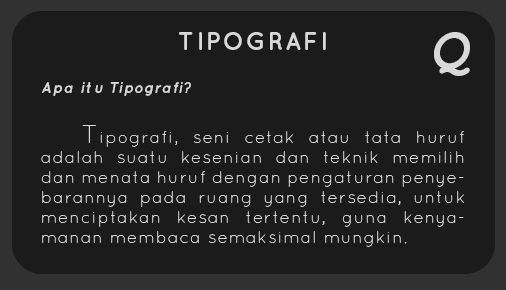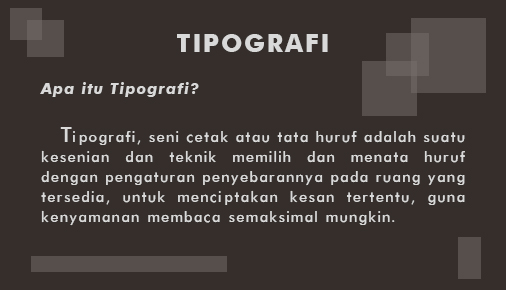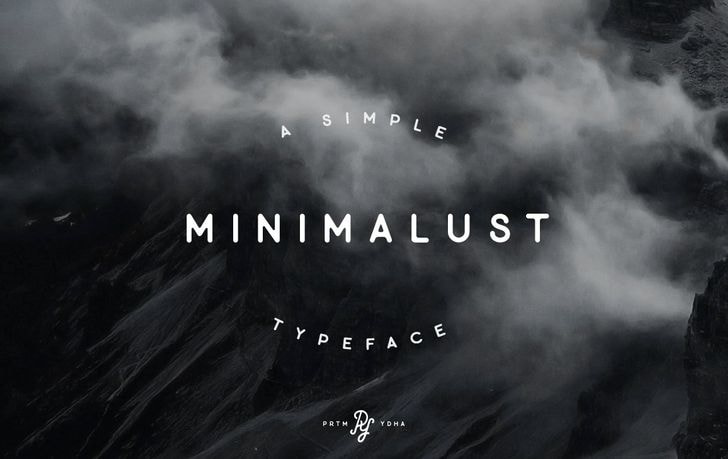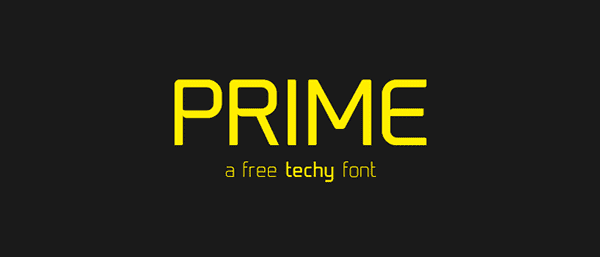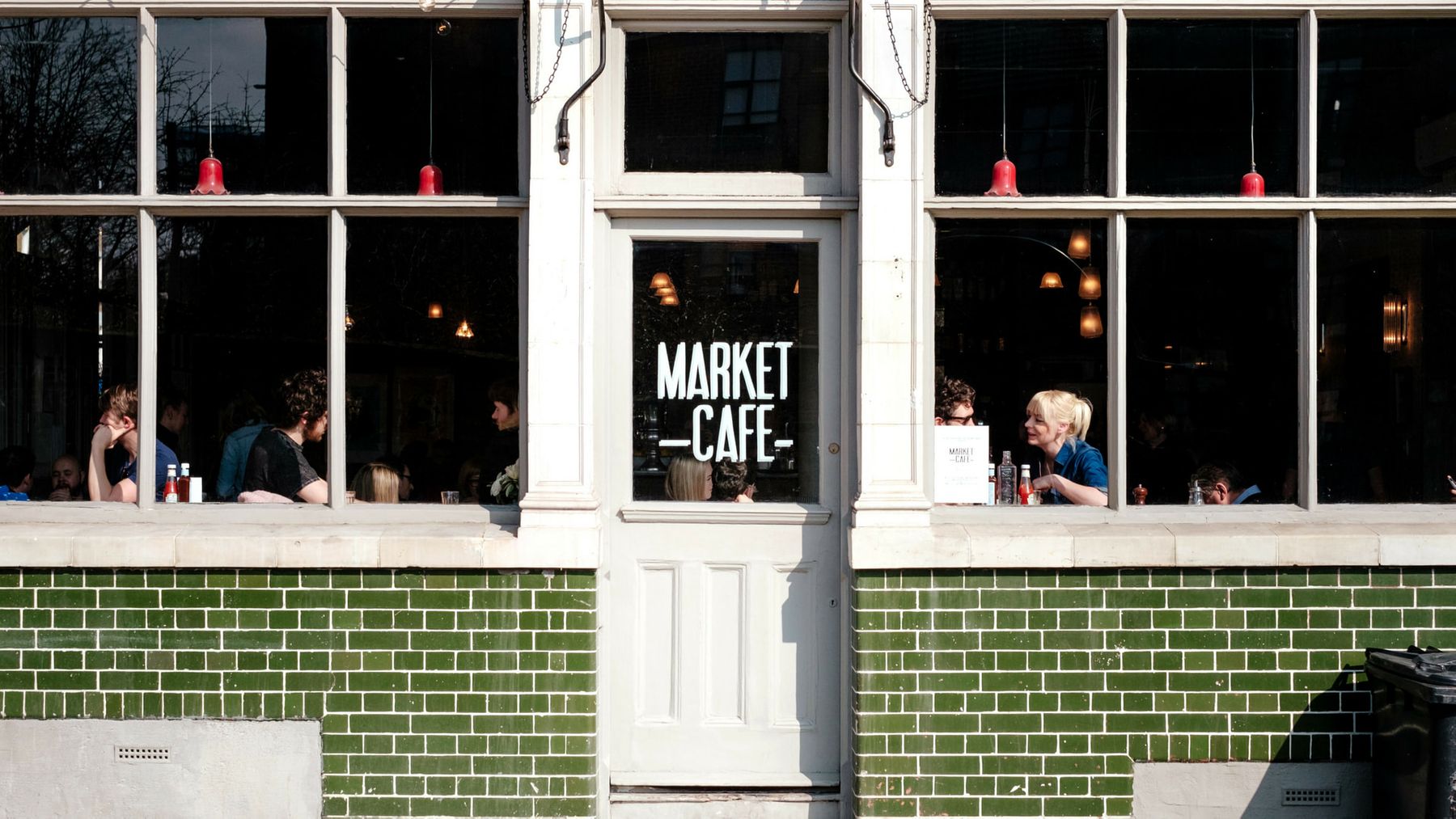
Font Tipografi Berkualitas Untuk Desain Korporasi Download Hereayuprint Co Id. Nah apa saja si jenis font yang bagus dan karakter jenis font itu seperti apa? Archive of freely downloadable fonts. Selain jenisnya yang cukup banyak, font serif juga dapat menyatu dengan gambar desain apa pun. Akula merupakan contoh yang bagus dari style tersebut. Semua 20 font yang bagus untuk poster ini bisa didownload langsung dari situs resminya. Bagi yang lagi proyek membuat poster, disarankan memilih salah satu font dibawah. Tentu sans serif merupakan font yang paling banyak digunakan dalam desain grafis. 1 2 3 4 5 6 7 8 9 10. Font merupakan kumpulan karakter huruf, angka, maupun simbol yang memiliki ukuran serta style tertentu. Font kuas kering merupakan tambahan yang bagus pada koleksimu untuk memasarkan material dan desain cetak. Browse by alphabetical listing, by style, by author or by popularity. Font serif ini memiliki rasa retro yang menyenangkan sembari mempertahankan gaya yang rumit. Pertemuan kali ini saya memberikan font gratis untukmu. Jenis huruf sans serif memiliki tepi yang sedikit tajam dan berstruktur geometris yang membuatnya fungsional dan. Simak kombinasi font yang bagus untuk website anda di ulasan kami dan alasan mengapa anda harus memilihnya, lengkap dengan contoh.
Tentu sans serif merupakan font yang paling banyak digunakan dalam desain grafis. Download free serif fonts for commercial and personal use. Lihat kombinasi font di atas, bagus bukan? Okomito disuntikkan dengan sentuhan tujuan, kejujuran, dan kekuatan industri. Andis adalah font yang terlihat bagus dalam semua ukuran. Free yang serif font is a handwritten utilitarian serif typeface that captures some essence of chinese calligraphy but no overly decretive by haoyang guan. Midline font duo is a two different font styles :
1 2 3 4 5 6 7 8 9 10. You can use these fonts to create custom styles. 1 2 3 4 5 6 7 8 9 10. Andis adalah font yang terlihat bagus dalam semua ukuran. Bagi yang lagi proyek membuat poster, disarankan memilih salah satu font dibawah. Contoh font serif adalah arial, verdana, calibri, dan trebuchet ms. Banyak sih sebenernya, jadi mungkin akan aku bagi jadi beberapa part okey?? Akula merupakan contoh yang bagus dari style tersebut. Simak kombinasi font yang bagus untuk website anda di ulasan kami dan alasan mengapa anda harus memilihnya, lengkap dengan contoh. Yang typeface is a hand written utilitarian serif typeface that captures some essence of chinese calligraphy but not overly decretive. Font yang bagus membuat semua perbedaan! These serif fonts are typically used in newspapers, because they make reading quick and easy. Download free serif fonts for commercial and personal use. Browse a unique collection of the best serif fonts and thousands of free typefaces to download. Ini beberapa font yang menurut aku bagus hehe. Midline font duo is a two different font styles : Lihat kombinasi font di atas, bagus bukan? Font ini membuat situs terasa hangat namun profesional. Serif adalah jenis font yang paling kuno, biasa. Jenis huruf sans serif memiliki tepi yang sedikit tajam dan berstruktur geometris yang membuatnya fungsional dan. Akagi | harganya sekitar $400 untuk 20 model. Font logo anda memainkan peran penting dalam membentuk citra bisnis anda. Serif typefaces have small projections at the ends of the letter strokes. Ini adalah jenis keluarga sans serif dengan enam bobot ditambah huruf miring yang cocok dan dirancang oleh hannes von döhren pada tahun 2009/10. Okomito disuntikkan dengan sentuhan tujuan, kejujuran, dan kekuatan industri. Bagai beliung dengan asahan, serif dan san serif tidak dapat dipisahkan kalau kita berbicara tentang kombinasi font terbaik. Please download and enjoy, or can search more similar fonts on demofont. Beberapa font yang bagus untuk desain website maupun desain aplication mobile yang gratis download, seni typography fonts, font pilihan untuk ini font web gratis yang diterbitkan di bawah lisensi open font sebuah font keluarga sans serif yang diciptakan oleh desainer polandia łukasz. Font serif adalah sebuah jenis font yang mempunyai kait, mata pancing atau sepatu di setiap ujung nya. Sangat jarang website yang menggunakan serif untuk font pada konten. Font serif ini memiliki rasa retro yang menyenangkan sembari mempertahankan gaya yang rumit.
50 Font Modern Yang Akan Memberikan Desain Anda Nuansa Kontemporer Canva. Nah apa saja si jenis font yang bagus dan karakter jenis font itu seperti apa? Jenis huruf sans serif memiliki tepi yang sedikit tajam dan berstruktur geometris yang membuatnya fungsional dan. Pertemuan kali ini saya memberikan font gratis untukmu. Bagi yang lagi proyek membuat poster, disarankan memilih salah satu font dibawah. Font serif ini memiliki rasa retro yang menyenangkan sembari mempertahankan gaya yang rumit. Simak kombinasi font yang bagus untuk website anda di ulasan kami dan alasan mengapa anda harus memilihnya, lengkap dengan contoh. Archive of freely downloadable fonts. Browse by alphabetical listing, by style, by author or by popularity. Akula merupakan contoh yang bagus dari style tersebut. 1 2 3 4 5 6 7 8 9 10. Semua 20 font yang bagus untuk poster ini bisa didownload langsung dari situs resminya. Font kuas kering merupakan tambahan yang bagus pada koleksimu untuk memasarkan material dan desain cetak. Font merupakan kumpulan karakter huruf, angka, maupun simbol yang memiliki ukuran serta style tertentu. Tentu sans serif merupakan font yang paling banyak digunakan dalam desain grafis. Selain jenisnya yang cukup banyak, font serif juga dapat menyatu dengan gambar desain apa pun.
30 Font Pilihan Terbaik Untuk Desain Grafis Gratis. 1 2 3 4 5 6 7 8 9 10. Selain jenisnya yang cukup banyak, font serif juga dapat menyatu dengan gambar desain apa pun. Nah apa saja si jenis font yang bagus dan karakter jenis font itu seperti apa? Tentu sans serif merupakan font yang paling banyak digunakan dalam desain grafis. Simak kombinasi font yang bagus untuk website anda di ulasan kami dan alasan mengapa anda harus memilihnya, lengkap dengan contoh. Font merupakan kumpulan karakter huruf, angka, maupun simbol yang memiliki ukuran serta style tertentu. Font kuas kering merupakan tambahan yang bagus pada koleksimu untuk memasarkan material dan desain cetak. Pertemuan kali ini saya memberikan font gratis untukmu. Semua 20 font yang bagus untuk poster ini bisa didownload langsung dari situs resminya. Browse by alphabetical listing, by style, by author or by popularity. Akula merupakan contoh yang bagus dari style tersebut. Bagi yang lagi proyek membuat poster, disarankan memilih salah satu font dibawah. Archive of freely downloadable fonts. Jenis huruf sans serif memiliki tepi yang sedikit tajam dan berstruktur geometris yang membuatnya fungsional dan. Font serif ini memiliki rasa retro yang menyenangkan sembari mempertahankan gaya yang rumit.
The style of this font are minimalist, signature, modern, elegant, luxury
Font Tipografi Berkualitas Untuk Desain Korporasi Download Hereayuprint Co Id. Font serif ini memiliki rasa retro yang menyenangkan sembari mempertahankan gaya yang rumit. Jenis huruf sans serif memiliki tepi yang sedikit tajam dan berstruktur geometris yang membuatnya fungsional dan. Tentu sans serif merupakan font yang paling banyak digunakan dalam desain grafis. Font kuas kering merupakan tambahan yang bagus pada koleksimu untuk memasarkan material dan desain cetak. Pertemuan kali ini saya memberikan font gratis untukmu. Selain jenisnya yang cukup banyak, font serif juga dapat menyatu dengan gambar desain apa pun. Bagi yang lagi proyek membuat poster, disarankan memilih salah satu font dibawah. Browse by alphabetical listing, by style, by author or by popularity. Akula merupakan contoh yang bagus dari style tersebut. Simak kombinasi font yang bagus untuk website anda di ulasan kami dan alasan mengapa anda harus memilihnya, lengkap dengan contoh. Nah apa saja si jenis font yang bagus dan karakter jenis font itu seperti apa? Font merupakan kumpulan karakter huruf, angka, maupun simbol yang memiliki ukuran serta style tertentu. Archive of freely downloadable fonts. Semua 20 font yang bagus untuk poster ini bisa didownload langsung dari situs resminya. 1 2 3 4 5 6 7 8 9 10.
7 Pilihan Terbaik Font Script Untuk Typography Kurnio Desain. Browse by alphabetical listing, by style, by author or by popularity. Font merupakan kumpulan karakter huruf, angka, maupun simbol yang memiliki ukuran serta style tertentu. Tentu sans serif merupakan font yang paling banyak digunakan dalam desain grafis. Archive of freely downloadable fonts. Font kuas kering merupakan tambahan yang bagus pada koleksimu untuk memasarkan material dan desain cetak. Font serif ini memiliki rasa retro yang menyenangkan sembari mempertahankan gaya yang rumit. Nah apa saja si jenis font yang bagus dan karakter jenis font itu seperti apa? Selain jenisnya yang cukup banyak, font serif juga dapat menyatu dengan gambar desain apa pun. Jenis huruf sans serif memiliki tepi yang sedikit tajam dan berstruktur geometris yang membuatnya fungsional dan. Akula merupakan contoh yang bagus dari style tersebut. Semua 20 font yang bagus untuk poster ini bisa didownload langsung dari situs resminya. Simak kombinasi font yang bagus untuk website anda di ulasan kami dan alasan mengapa anda harus memilihnya, lengkap dengan contoh. 1 2 3 4 5 6 7 8 9 10. Bagi yang lagi proyek membuat poster, disarankan memilih salah satu font dibawah. Pertemuan kali ini saya memberikan font gratis untukmu.
Kenali Jenis Font Dalam Desain Grafis Saveas Brand Blog Artikel Desain Grafis Dan Komunikasi. 1 2 3 4 5 6 7 8 9 10. Bagi yang lagi proyek membuat poster, disarankan memilih salah satu font dibawah. Tentu sans serif merupakan font yang paling banyak digunakan dalam desain grafis. Semua 20 font yang bagus untuk poster ini bisa didownload langsung dari situs resminya. Browse by alphabetical listing, by style, by author or by popularity. Simak kombinasi font yang bagus untuk website anda di ulasan kami dan alasan mengapa anda harus memilihnya, lengkap dengan contoh. Font merupakan kumpulan karakter huruf, angka, maupun simbol yang memiliki ukuran serta style tertentu. Pertemuan kali ini saya memberikan font gratis untukmu. Archive of freely downloadable fonts. Akula merupakan contoh yang bagus dari style tersebut. Selain jenisnya yang cukup banyak, font serif juga dapat menyatu dengan gambar desain apa pun. Font serif ini memiliki rasa retro yang menyenangkan sembari mempertahankan gaya yang rumit. Jenis huruf sans serif memiliki tepi yang sedikit tajam dan berstruktur geometris yang membuatnya fungsional dan. Nah apa saja si jenis font yang bagus dan karakter jenis font itu seperti apa? Font kuas kering merupakan tambahan yang bagus pada koleksimu untuk memasarkan material dan desain cetak.
Tentu sans serif merupakan font yang paling banyak digunakan dalam desain grafis.
Font Tipografi Berkualitas Untuk Desain Korporasi Download Hereayuprint Co Id. Bagi yang lagi proyek membuat poster, disarankan memilih salah satu font dibawah. Font merupakan kumpulan karakter huruf, angka, maupun simbol yang memiliki ukuran serta style tertentu. Font serif ini memiliki rasa retro yang menyenangkan sembari mempertahankan gaya yang rumit. Akula merupakan contoh yang bagus dari style tersebut. Semua 20 font yang bagus untuk poster ini bisa didownload langsung dari situs resminya. Browse by alphabetical listing, by style, by author or by popularity. Tentu sans serif merupakan font yang paling banyak digunakan dalam desain grafis. 1 2 3 4 5 6 7 8 9 10. Pertemuan kali ini saya memberikan font gratis untukmu. Nah apa saja si jenis font yang bagus dan karakter jenis font itu seperti apa? Font kuas kering merupakan tambahan yang bagus pada koleksimu untuk memasarkan material dan desain cetak. Archive of freely downloadable fonts. Simak kombinasi font yang bagus untuk website anda di ulasan kami dan alasan mengapa anda harus memilihnya, lengkap dengan contoh. Selain jenisnya yang cukup banyak, font serif juga dapat menyatu dengan gambar desain apa pun. Jenis huruf sans serif memiliki tepi yang sedikit tajam dan berstruktur geometris yang membuatnya fungsional dan.
Selain jenisnya yang cukup banyak, font serif juga dapat. Free yang serif font is a handwritten utilitarian serif typeface that captures some essence of chinese calligraphy but no overly decretive by haoyang guan. Font serif ini memiliki rasa retro yang menyenangkan sembari mempertahankan gaya yang rumit. Font ini membuat situs terasa hangat namun profesional. Memilih font yang baik untuk digunakan dalam kutipan anda memastikan dokumen yang mudah dibaca dan profesional. list font yang bagus (1). Font futura yang bold akan dinetralisir oleh font souvenir yang jauh lebih ringan. Jenis huruf sans serif memiliki tepi yang sedikit tajam dan berstruktur geometris yang membuatnya fungsional dan. Website ini menggunakan font lato sans serif yang didesain oleh warsaw dan łukasz dziedzic. You can use these fonts to create custom styles.